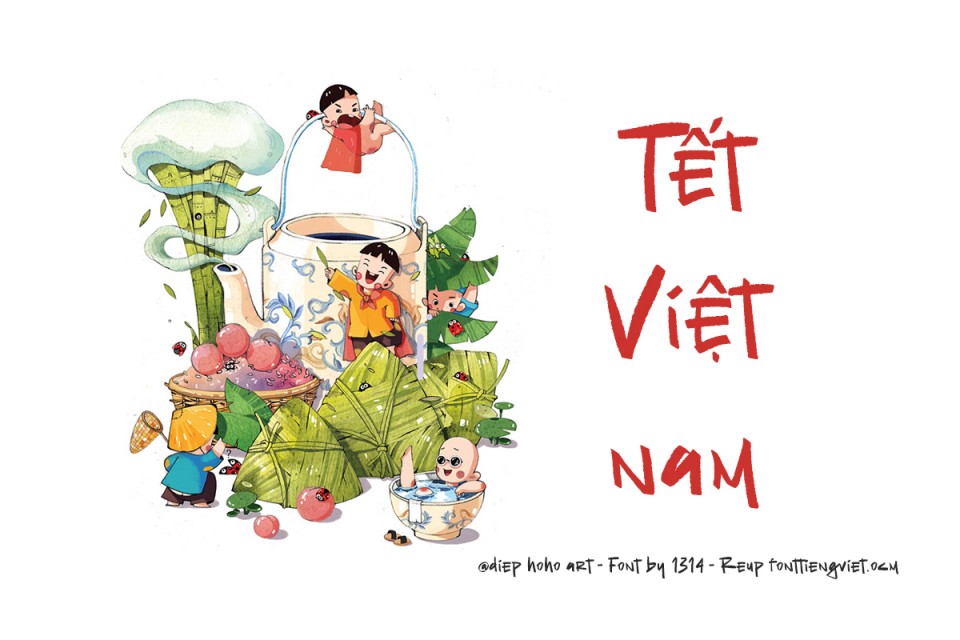
Mô tả về Việt hóa font 1314 The Old Falcons và font Tết
1. Font 1314 The Old Falcons
Font 1314 The Old Falcons là một kiểu chữ được thiết kế với phong cách cổ điển, mang lại cảm giác sang trọng và quý phái. Việt hóa font này bao gồm việc bổ sung các ký tự tiếng Việt như chữ có dấu (â, ê, ô, ư, đ…) để người dùng có thể sử dụng trong các văn bản tiếng Việt mà không làm mất đi tính thẩm mỹ của font chữ.
2. Font Tết
Font Tết thường được sử dụng trong các dịp lễ Tết Nguyên Đán, mang đậm nét văn hóa truyền thống của người Việt. Kiểu chữ này thường có thiết kế vui tươi, nhấn mạnh vào các yếu tố như hoa mai, hoa đào, hay hình ảnh chúc Tết. Việt hóa font Tết không chỉ giúp hiển thị các ký tự tiếng Việt mà còn có thể bổ sung các yếu tố trang trí đặc trưng của Tết, tạo nên sự hấp dẫn cho các sản phẩm đồ họa, thiệp chúc mừng hay banner quảng cáo trong dịp lễ này.
Kết luận
Việt hóa các font như 1314 The Old Falcons và font Tết là việc cần thiết để đáp ứng nhu cầu sử dụng tiếng Việt trong thiết kế đồ họa, đồng thời giữ gìn bản sắc văn hóa và phong cách riêng biệt của ngôn ngữ.